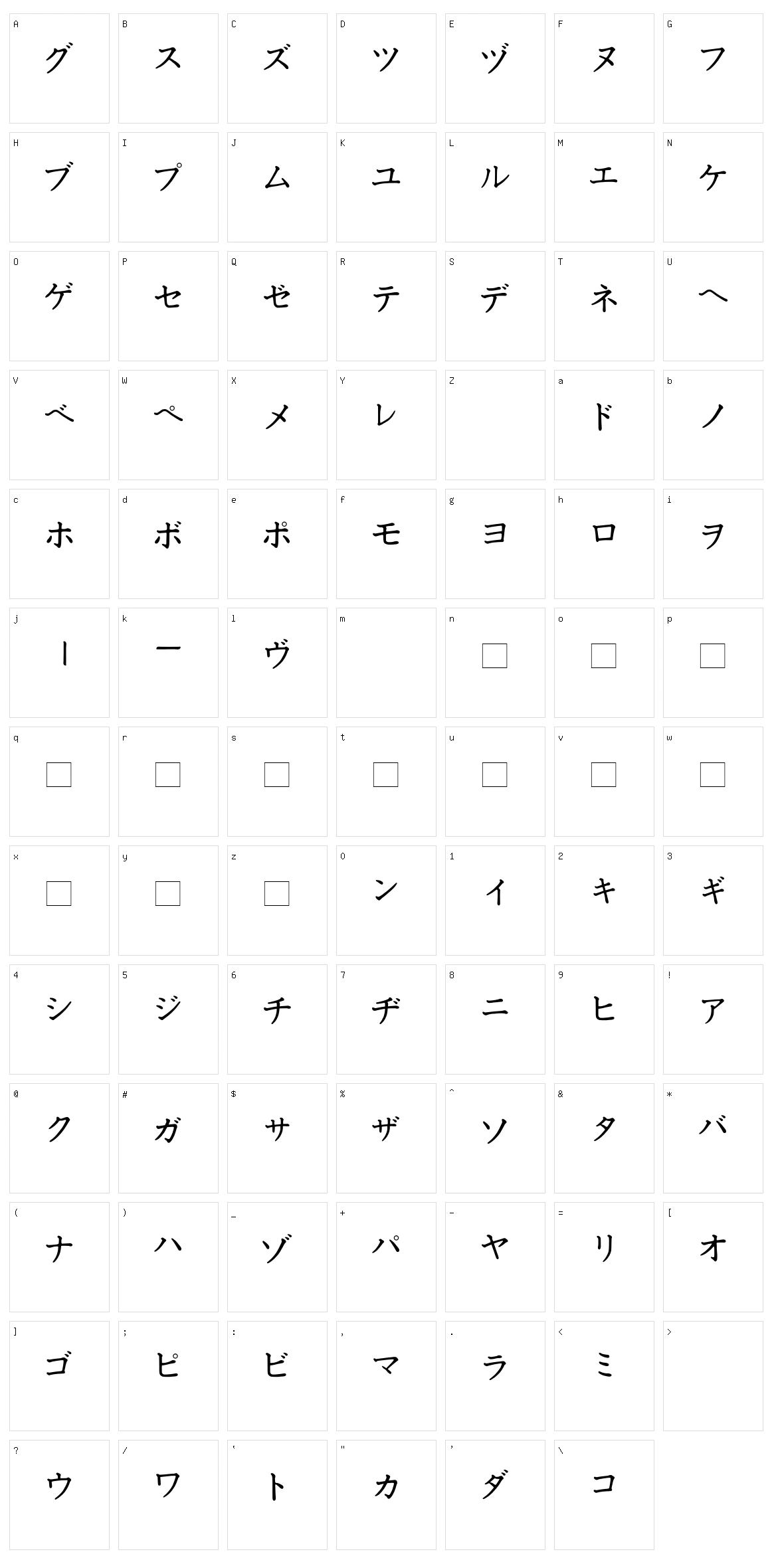
La police de charactère Katakana prend en compte le
syllabaire japonais de base, servant à retranscrire
les mots d'origine étrangère
Comme il prend en compte les syllabes disparues, il est donc complet